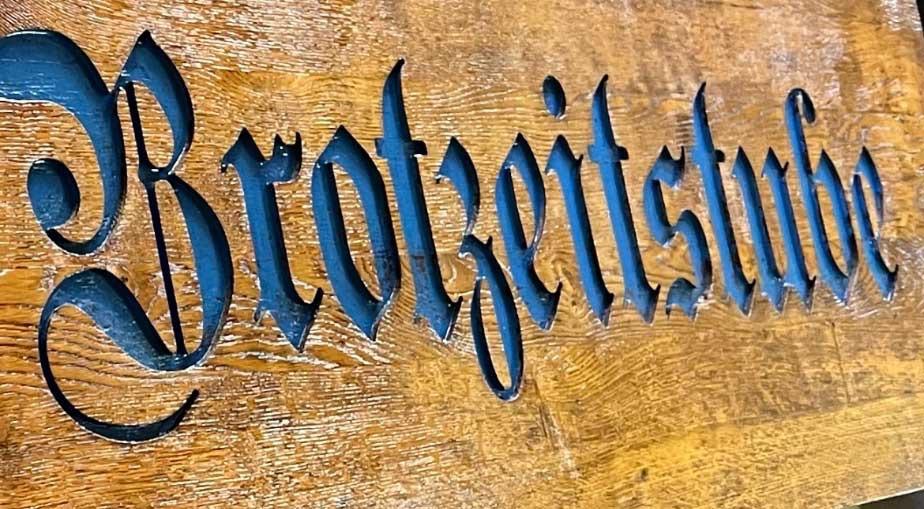
Font von Brotzeitstubenschild
Hallo Zusammen! Ein Schreiner hat für sich dieses alte Schild für seine Brotzeitstube gemacht. Jetzt heißt meine zu vermietende Ferienwohnung so und ich brauche noch 3 kleinere Schilder zur Orientierung der Gäste. Er weiß aber den Namen der Fraktur leider nicht mehr. Kann mir da jemand sagen, welche Schriftart oder wie genau der Name ist.
sh BILD des Original
Eine perspektivisch unverzerrte, sprich: frontale (und vollständige) Aufnahme des Schriftzug würde den Fraktur-Experten hier im Forum die Identifikation bestimmt deutlich erleichtern.